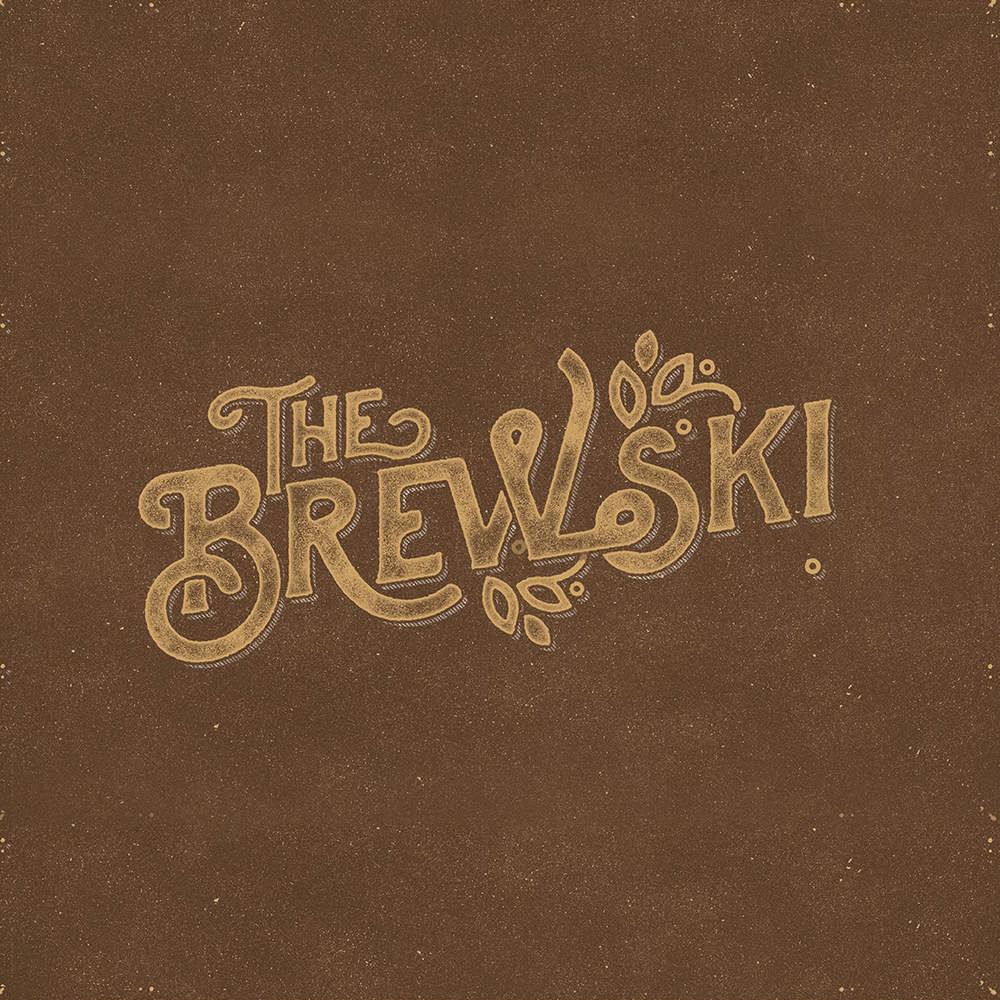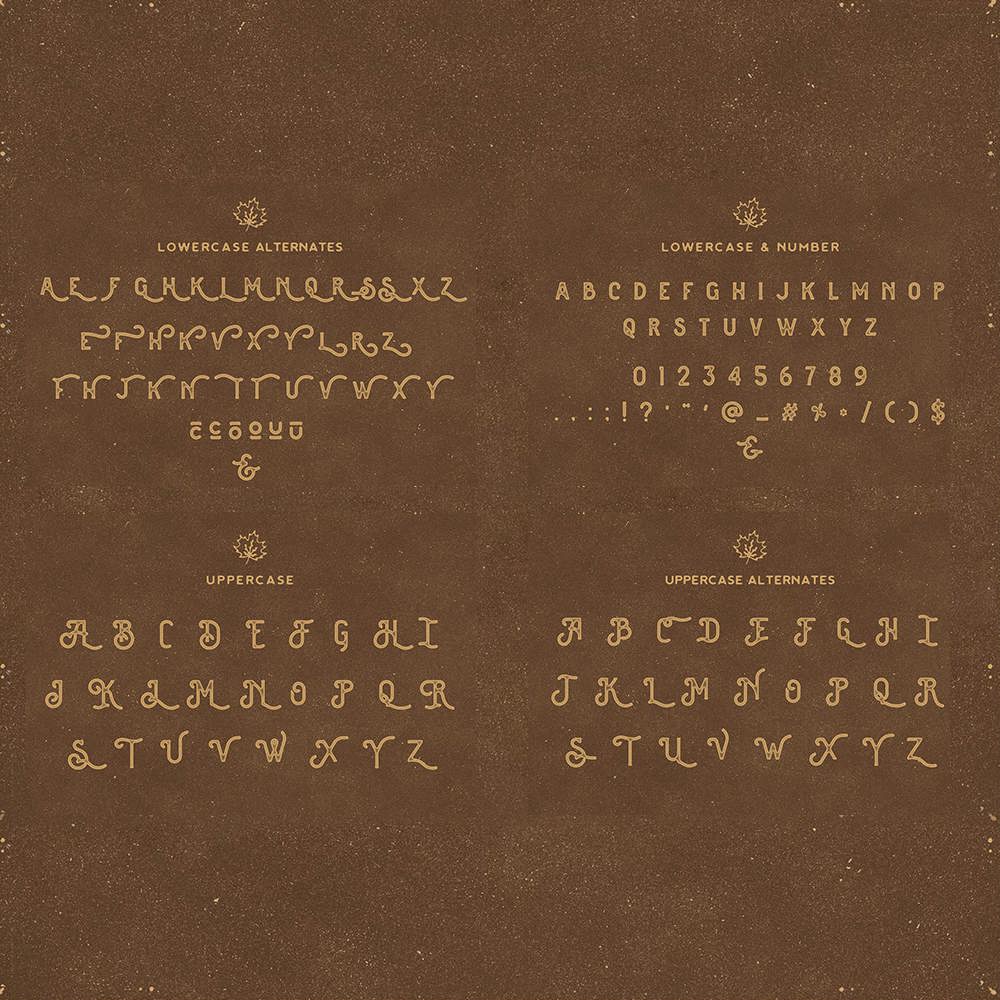
فونت پرمیوم و انگلیسی The Brewski Font یک فونت بافتدار است، با ترکیبی از انواع کاراکترها و تزئینات متعدد که به این فونت ظاهری سبکی میبخشد. با الهام از بستهبندیهای قدیمی کارخانههای آبجوسازی و تبلیغات آبجو از اوایل قرن بیستم. این فونت برای طراحی لوگوهای قدیمی، تیترها یا بستهبندیها عالی است. Brewski با انواع سبکی و متنی در کاراکترهای خاص طراحی کرده است و به شما این امکان را میدهد که جفت حروف را با هم ترکیب و مطابقت دهید تا با طراحی شما مطابقت داشته باشد. این فونت برای طراحیهای قدیمی، تیشرتها، لوگوها، برچسبها، پوسترها و موارد دیگر ایدهآل است.
مزایای استفاده از فونت لاتین The Brewski چیست؟